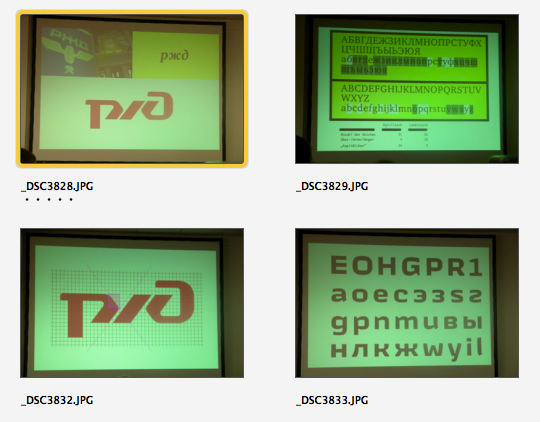
Schrift der neuen RZD-Zuglaufschilder
Die Russische Eisenbahn ??? hat zum fahrplanwechsel im dezember 2007 ein neues design der zuglaufschilder eingeführt. Neue destinationen (Paris, Basel, München, Amsterdam) kamen auch dazu.
Die schrift enthält kyrillische und lateinische großbuchstaben. Kann sie jemand identifizieren? Gibt es die irgendwo zum kauf/download? Dann muss ich sie nicht nachzeichnen.
Das wird wohl die neue Schrift sein die Herr Lavrow als Preview auf den TypoTagen 2007 (Leipzig) gezeigt hat. Sie sieht aber jetzt rundlicher aus. Wenn du es ganz genau wissen willst, einfach mal ihn fragen. http://www.hardcase.de
Von dieser neuen hausschrift scheint es mehrere varianten zu geben:
Die kyrillischen kleinbuchstaben gibt es in abweichenden kursiven formen, die laut http://de.wikipedia.org/wiki/Kyrillisches_Alphabet#Kursive_und_aufrechte_Formen im bulgarischen und serbischen auch in aufrechter schrift verwendet werden. Die untere variante der buchstaben scheint im russischen die geläufigere zu sein, allerdings reichen meine kenntnisse in der russischen sprache und schrift nicht aus, um das wirklich einschätzen zu können. Welche version wird die RZD nun auf dauer verwenden?